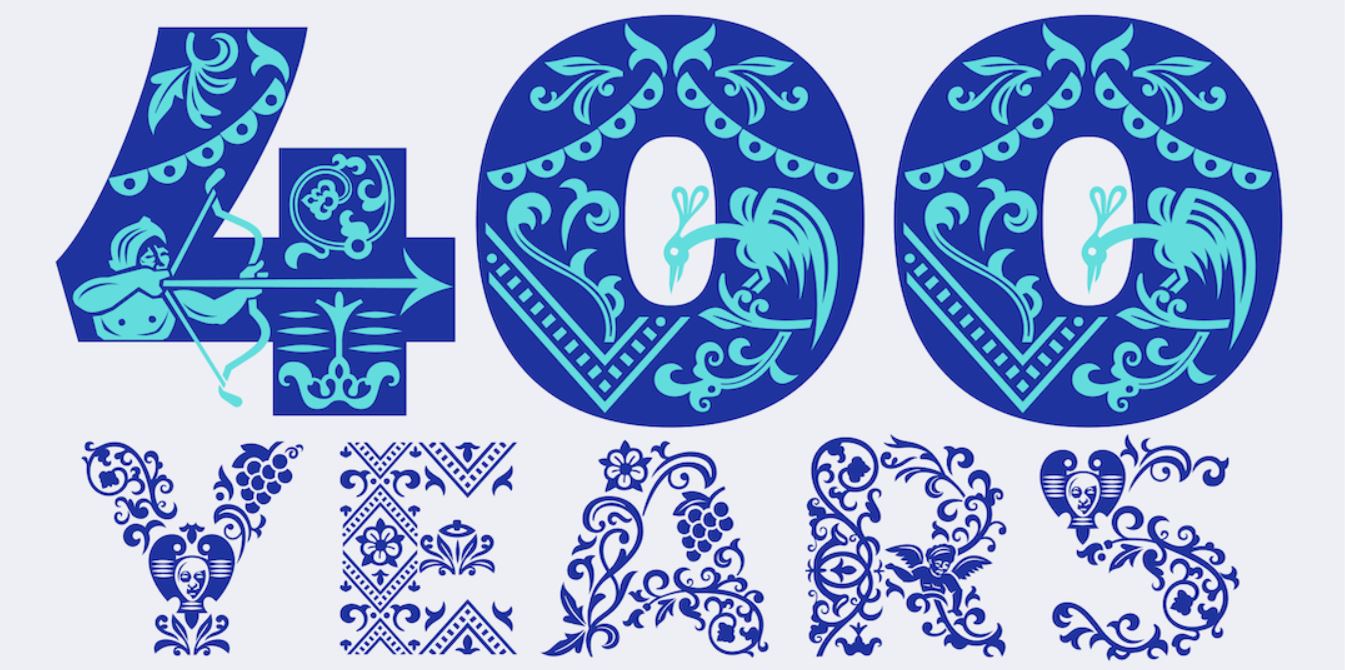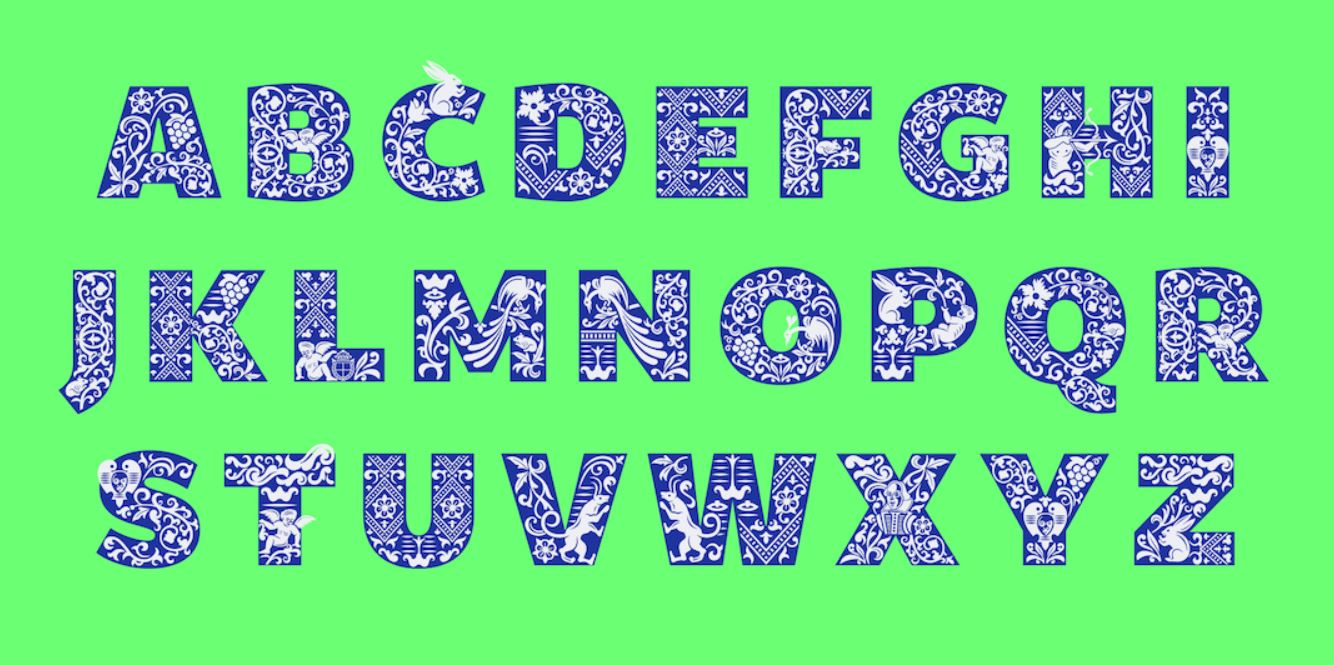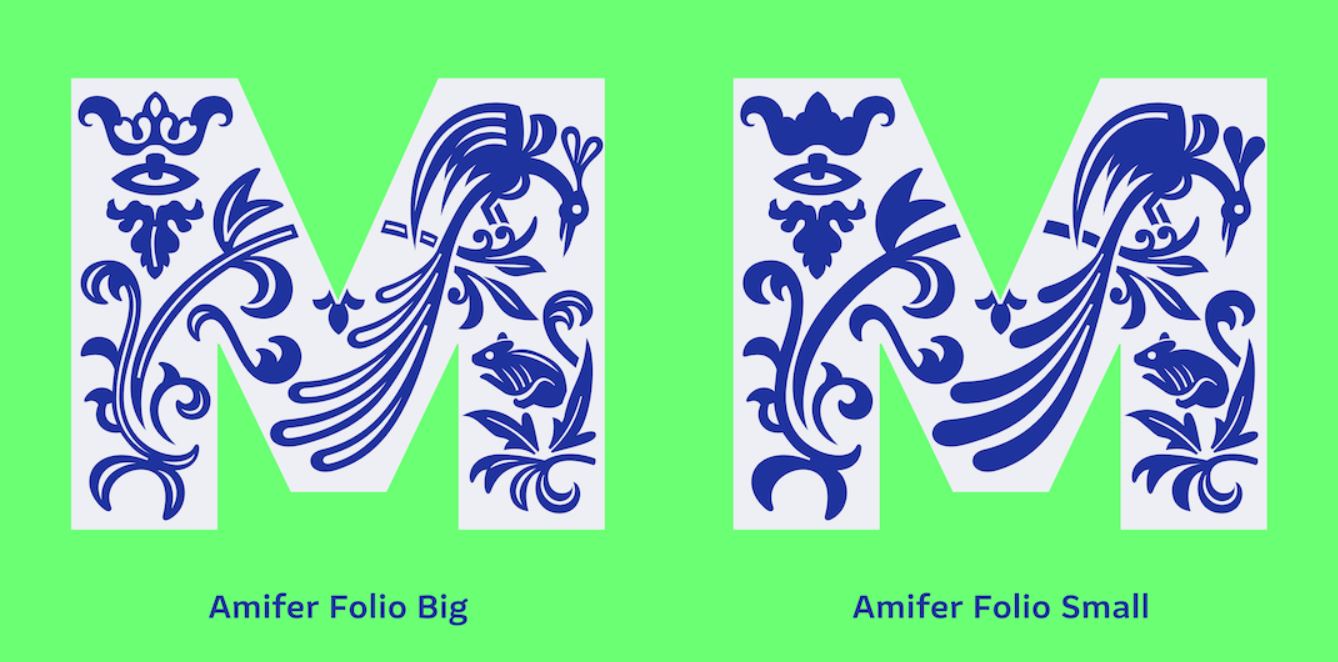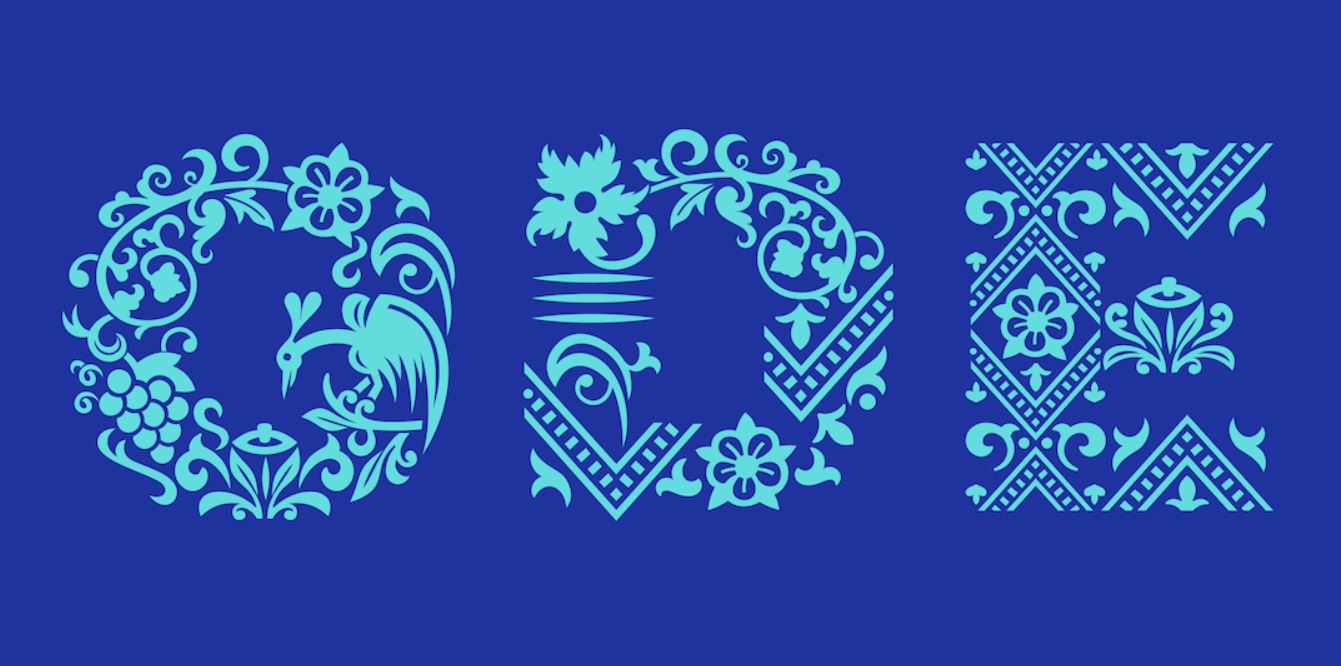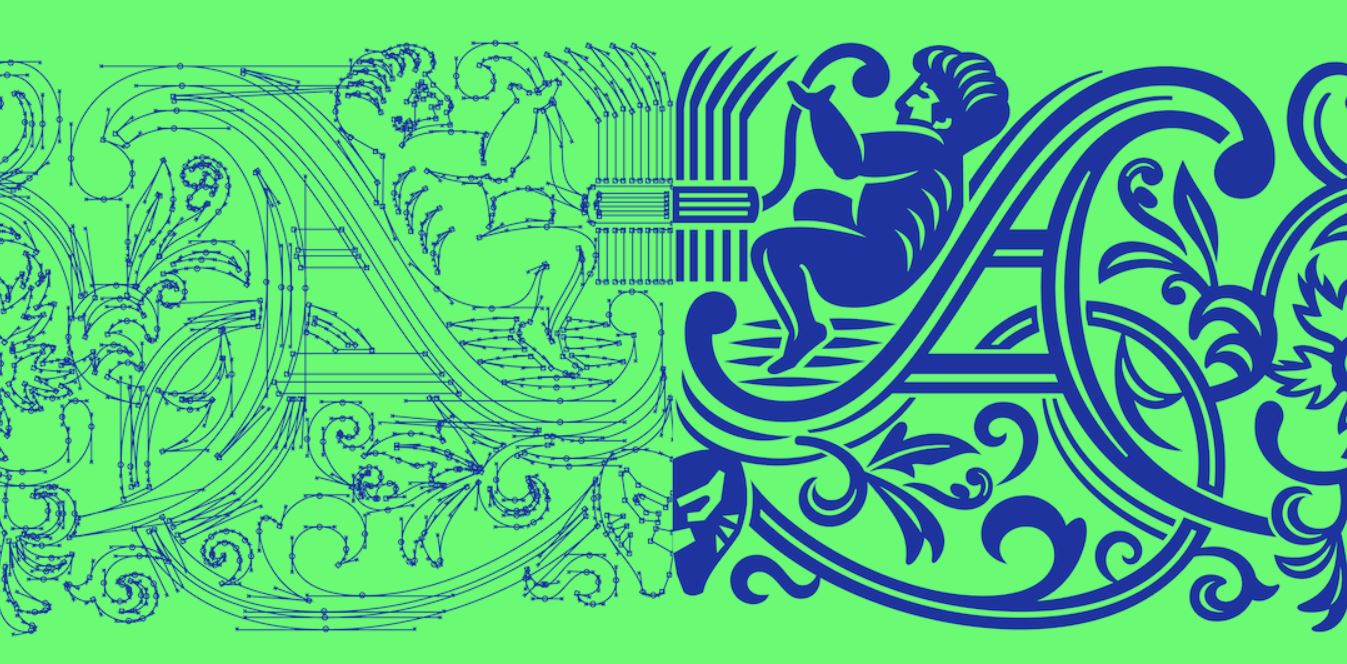
First Folio-ს, ანუ უილიამ შექსპირის პიესების პირველი კრებულის, 400 წლის აღსანიშნავად, Shakespeare’s Globe-მა ახალი ფონტი გამოუშვა. გამოცემა ისეთ ნამუშევრებს მოიცავს, როგორებიცაა მაკბეტი და ქარიშხალი — შესაბამისად, ის ერთ-ერთი ყველაზე ძვირფასია ლიტერატურის ისტორიაში.
Typeland-ის მიერ შემუშავებული ფონტი კრებულში შემავალი პიესების სახასიათო დეტალებს აერთიანებს. მაგალითისთვის, ვხედავთ ზაფხულისთვის თემატურ ელემენტებს, „აყვავებისა და დაშლის იდეებს, ასევე რეგენერაციის ციკლებსა და ბალანსის აღდგენას“. Design Week-ის მიხედვით, ორნამენტირებული ასოების დიდხნიანი ტრადიცია არსებობს — ფონტის ამგვარ სტილში გამოყენებულია ხილის, ყვავილების, ველური ბუნებისა და მუსიკალური ინსტრუმენტების ვიზუალები.
ამ კონკრეტულ შემთხვევაში სტუდია უშუალოდ First Folio-ზე ფოკუსირდა, ისტორიული კრებულის ინტერპრეტაციას მიმართა და თანამედროვე მანერას მოარგო.